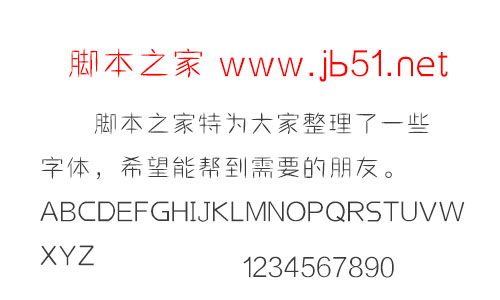
幾何刀刃體是一款非常不錯(cuò)的藝術(shù)字體,工整簡(jiǎn)潔,具有強(qiáng)烈的視覺(jué)沖擊力,適應(yīng)于報(bào)紙和雜志和書籍中常用字體, 海報(bào)、個(gè)性促進(jìn)品牌標(biāo)志設(shè)計(jì)、字體設(shè)計(jì)、等環(huán)境使用,歡迎喜歡幾何刀刃體的朋友前來(lái)下載使用。